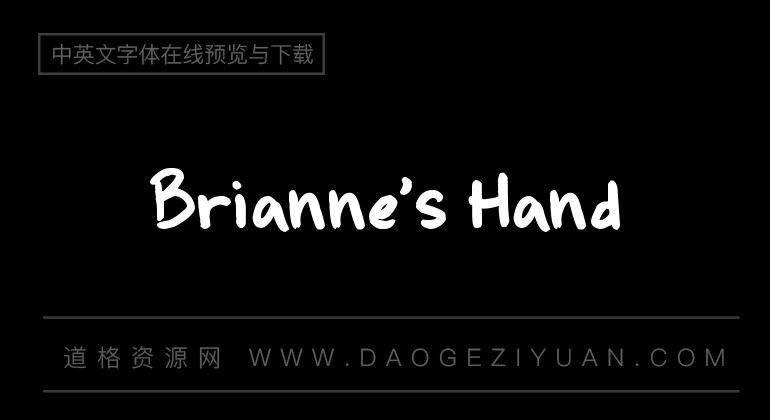
? Brianne's Hand是一款手写体字体,它的特点是每个字母都有一种独特的手写风格,这种风格有一种柔和的质感,它的字体很容易看清楚,使它成为一个完美的手写字体。它的字体很容易看清楚,它的字体也有一种柔和的质感,它的字体也有一种古典的风格,它也可以用于网页设计,报纸,印刷品,书籍,海报等。内容介绍
Brianne's Hand是一款非常不错的手写艺术字体,具有很好的视觉感,适合于文化类的宣传设计、商业类品牌的广告和产品包装设计以及个性化文字排版等较多场景。